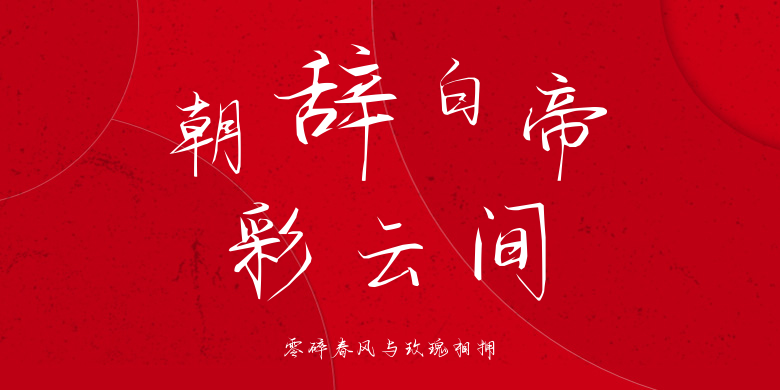
零碎春风与玫瑰相拥
零碎春风与玫瑰相拥,这款字体结构工整、笔画清晰,兼顾美观与易读性,适用于标题、正文、海报、包装、LOGO 等多种场景。字形优雅稳定,风格百搭耐看,适配日常排版与创意设计,让文字呈现更舒适、更具质感。零碎春风与玫瑰相拥一笔一画,皆是细节,以均衡的比例、流畅的线条打造舒适视觉体验,字形端正大气,风格简约现代。无论是商业设计、品牌宣传还是日常排版,都能轻松驾驭,让文字更有格调与力量。零碎春风与玫瑰相拥字体下载。